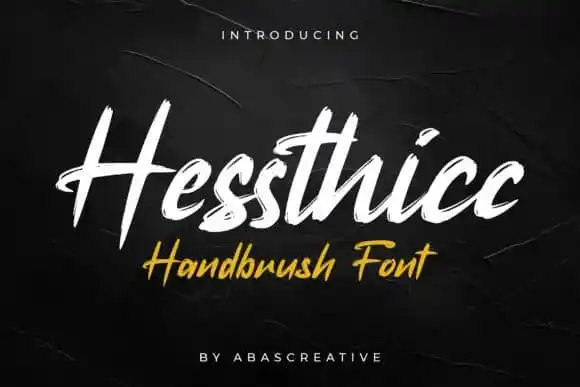
Hessthicc Brush Font – Download Grátis
A Hessthicc Brush Font é uma fonte tipo que foi especialmente criada para quem ama estilos cômico e cartoon. Desenvolvida por AbasCreative no site de design 99designs, esta tipografia traz uma paleta espetacular entre um caneta-pen e um lápis. O resultado é um estilo extremamente encantador e autêntico, perfeito para adicionar uma pitada divertida em vários projetos gráficos. Este tipo de fonte pode ser usada com facilidade em diversos tipos de trabalho gráfico, como logotipos, camisetas, capas de álbuns, posters, rótulos, tipografia, identidades corporativas, revistas e anúncios. Seus traços brincalhões e fluidos a tornam não só versáteis, mas também ideal para aqueles projetos que precisam um toque descontraído sem abrir mão da qualidade. A Hessthicc Brush Font é perfeita tanto para designers iniciantes quanto profissionais experientes, já que se adapta facilmente ao seu estilo de trabalho. Se você está procurando por uma fonte fresca e divertida, sem perder a qualidade ou a consistência em seus projetos, esta pode ser sua escolha ideal. Não hesite em experimentar!